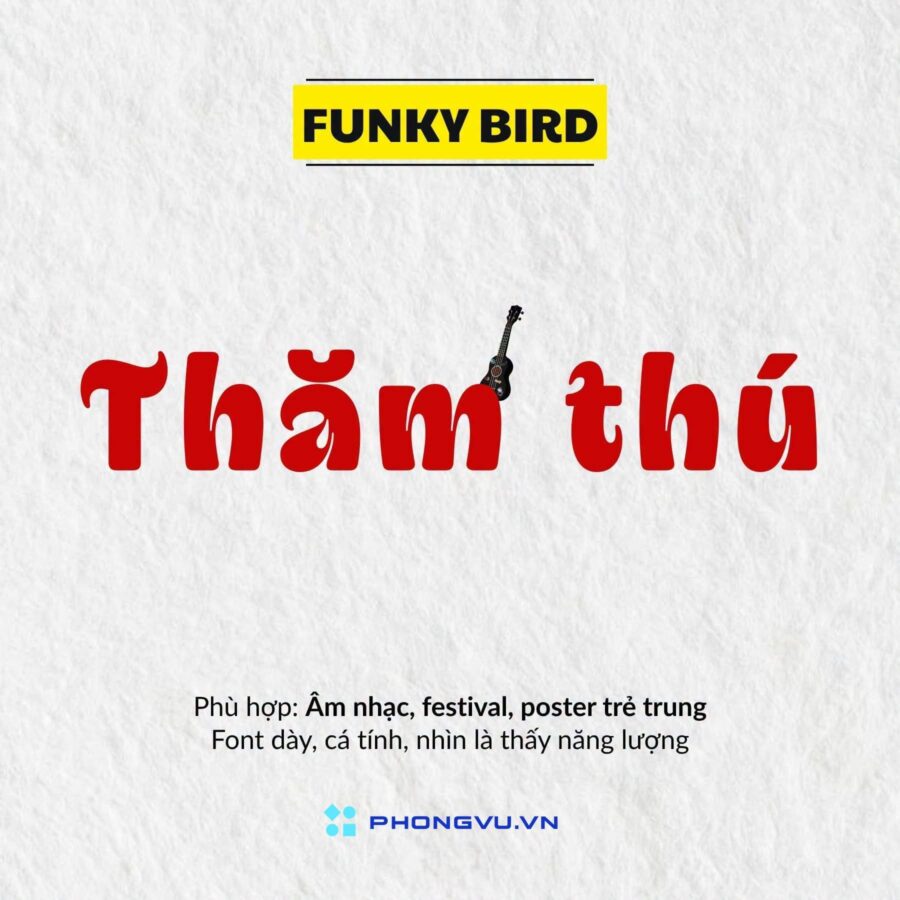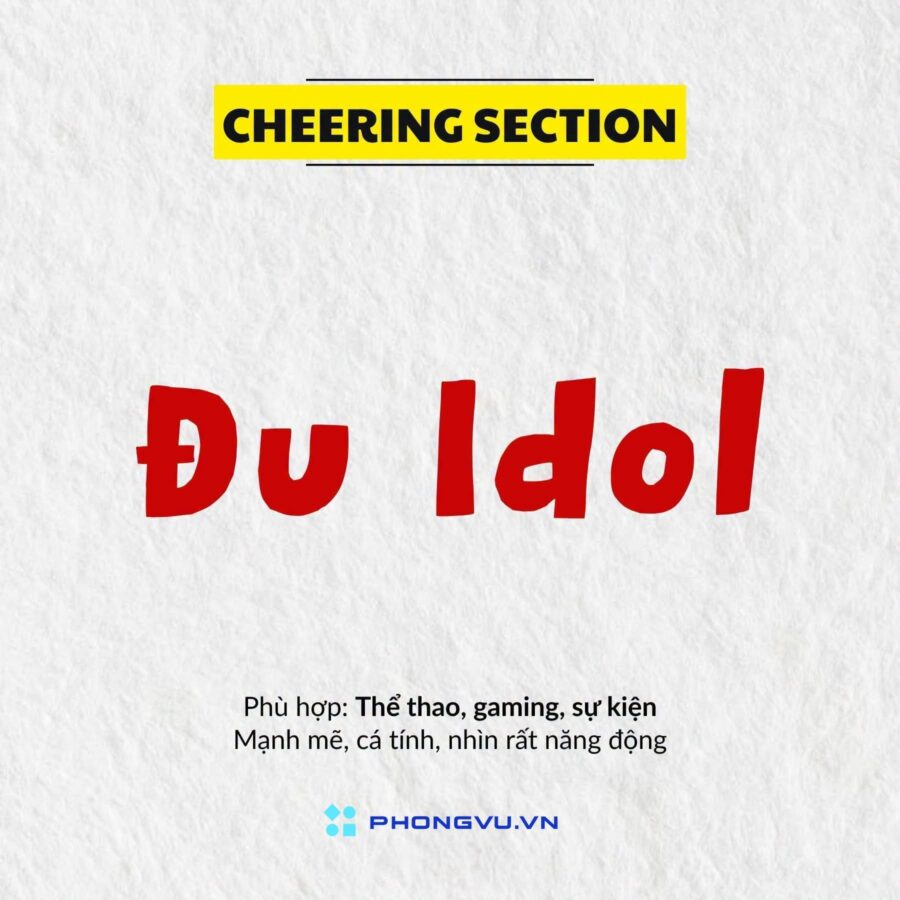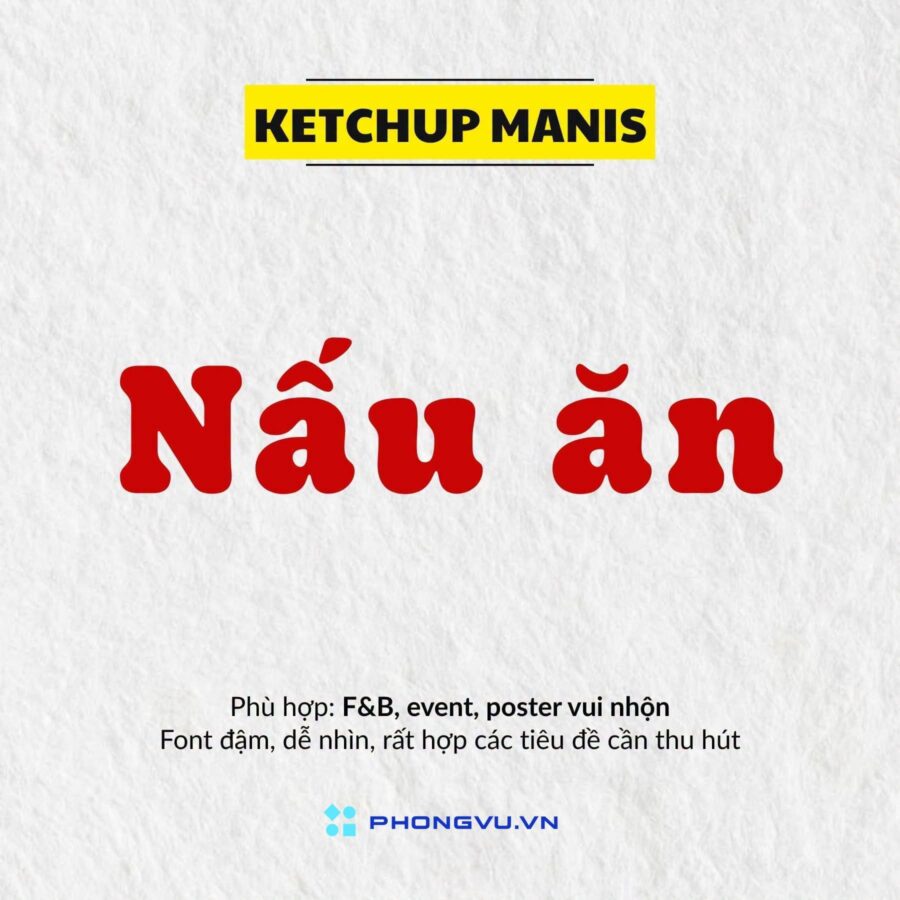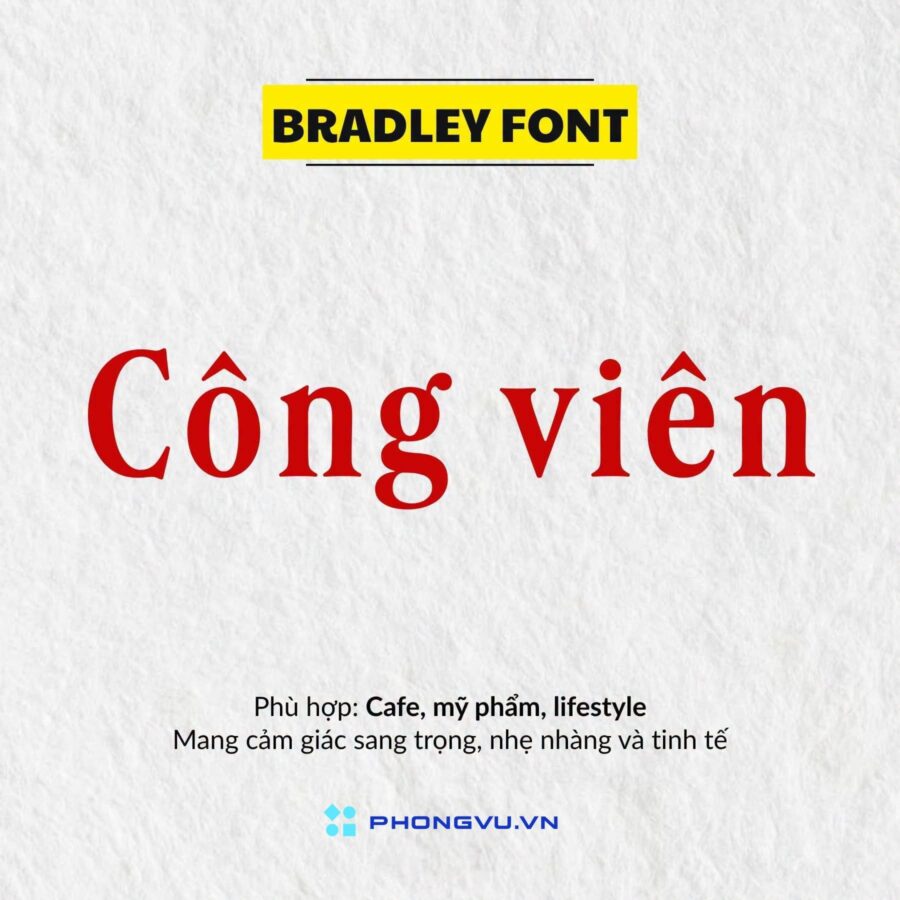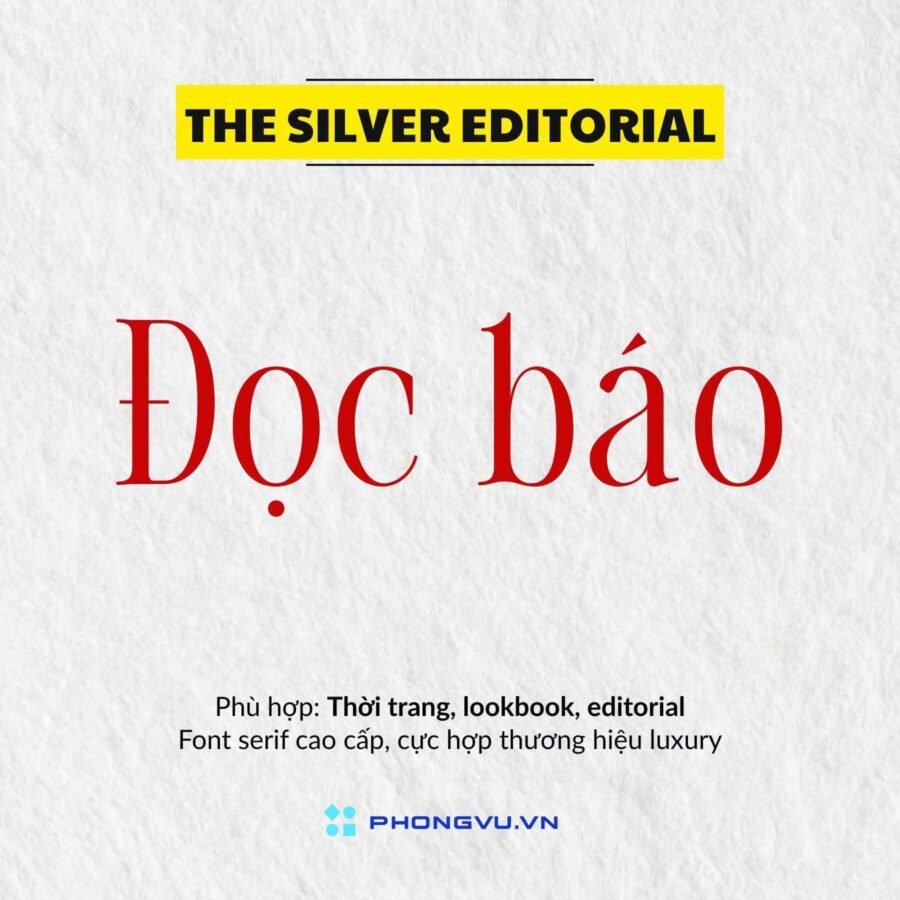
Bạn đang tìm kiếm những font chữ Việt hóa trên Canva đẹp, độc đáo và dễ sử dụng trên để nâng tầm thiết kế của mình? Với sự phát triển không ngừng của nền tảng Canva và nhu cầu sáng tạo nội dung ngày càng cao, việc sở hữu những font chữ chất lượng không chỉ giúp bạn thể hiện phong cách cá nhân mà còn tối ưu hóa trải nghiệm người xem. Trong bài viết này, Phong Vũ Tech News đã tổng hợp và chọn lọc danh sách 111+ font chữ Việt hóa mới nhất năm 2026, đảm bảo đáp ứng mọi nhu cầu từ thiết kế thương hiệu, bài thuyết trình, đến các dự án nghệ thuật. Hãy cùng khám phá để làm mới kho ý tưởng của bạn ngay hôm nay!
I. Top các Font chữ Việt hóa trên Canva đẹp, chuyên nghiệp
Trong kho tàng font chữ phong phú của Canva, việc tìm ra những font chữ Việt hóa vừa đẹp mắt, vừa chuyên nghiệp đôi khi có thể khiến bạn bối rối. Để giúp bạn tiết kiệm thời gian và tối ưu hóa thiết kế của mình, chúng tôi đã lựa chọn những font chữ Việt hóa trên Canva nổi bật nhất, phù hợp với nhiều phong cách và mục đích sử dụng như sau:
- Amatic SC
- Pacifico
- Coiny
- Vollkorn
- Blacker Sans Text
- Mali
- Dancing Script
- Noto serif display black
- Bahianita
- Sigmar one
Từ những font thanh lịch dành cho thương hiệu cao cấp, đến các kiểu chữ sáng tạo cho bài thuyết trình hay nội dung truyền thông mạng xã hội, danh sách tên sẽ là người bạn đồng hành không thể thiếu cho các dự án của bạn.
III. Bí quyết tìm các Font chữ Việt hóa trên Canva đẹp nhất
Việc lựa chọn font chữ phù hợp có thể quyết định phần lớn thành công của thiết kế. Đặc biệt, với những font chữ Việt hóa, yếu tố thẩm mỹ và hỗ trợ tiếng Việt đầy đủ là rất quan trọng. Dưới đây là những bí quyết giúp bạn dễ dàng tìm được các font chữ Việt hóa trên Canva đẹp và ấn tượng nhất:
- Bước 1: Tìm kiếm bằng từ khóa: Gõ “Sans Serif” hoặc “Slab Serif” vào ô tìm kiếm. Trong đó, Sans Serif: Font không có chân, thường dùng cho thiết kế hiện đại, trẻ trung. Slab Serif: Font có chân vuông, tạo cảm giác chắc chắn, chuyên nghiệp. Đây là hai loại font phổ biến và dễ đọc với tiếng Việt.
- Bước 2: Chọn font ưng ý: Canva sẽ hiển thị nhiều tùy chọn. Bạn có thể lọc theo độ đậm nhạt, kiểu chữ (in hoa, thường) để tìm font phù hợp nhất.
IV. Một số câu hỏi thường gặp về các Font chữ Việt hóa trên Canva
Trong quá trình thiết kế, đặc biệt khi sử dụng các font chữ Việt hóa trên Canva, bạn có thể gặp một số thắc mắc về cách chọn font, xử lý lỗi hoặc tùy chỉnh font theo ý muốn. Dưới đây, chúng tôi đã tổng hợp và giải đáp những câu hỏi thường gặp nhất để giúp bạn dễ dàng hơn trong việc sử dụng font chữ trên Canva:
1. Font chữ Việt hóa trên Canva và chưa Việt hóa có gì khác nhau?
Font chữ Việt hóa là những font đã được điều chỉnh để hỗ trợ đầy đủ các ký tự tiếng Việt, bao gồm cả các dấu (sắc, huyền, hỏi, ngã, nặng) và chữ cái đặc biệt như “ă”, “â”, “ê”, “đ”,… Những font này đảm bảo tính thẩm mỹ, độ cân đối khi sử dụng cho văn bản tiếng Việt.
Ngược lại, font chưa Việt hóa thường chỉ hỗ trợ ký tự cơ bản của bảng chữ cái tiếng Anh. Khi sử dụng cho tiếng Việt, các dấu và chữ cái đặc biệt có thể bị lỗi như mất nét, hiển thị không đồng đều hoặc thay bằng ký tự lạ. Điều này làm giảm chất lượng thiết kế và tính chuyên nghiệp của sản phẩm.
2. Làm sao để Việt hóa font chữ trên Canva?
Hiện tại, Canva chưa có tính năng trực tiếp để Việt hóa font chữ. Tuy nhiên, bạn có thể thực hiện theo các cách sau:
- Tìm bản Việt hóa của font chữ: Rất nhiều nhà thiết kế và cộng đồng trực tuyến đã Việt hóa các font phổ biến. Hãy tìm kiếm tên font kèm từ khóa “Việt hóa” để tải về phiên bản hỗ trợ tiếng Việt.
- Sử dụng font chữ Việt hóa có sẵn: Canva cung cấp một kho font chữ khổng lồ, trong đó có nhiều font chữ Việt hóa đẹp mắt. Bạn chỉ cần tìm kiếm và chọn font chữ phù hợp với thiết kế của mình.
- Tải font chữ Việt hóa lên Canva: Nếu bạn có font chữ Việt hóa yêu thích, bạn có thể tải lên Canva để sử dụng. Tuy nhiên, tính năng này thường chỉ dành cho các tài khoản Canva Pro hoặc các gói cao cấp hơn.
3. Làm sao để tải font chữ lên Canva?
Nếu bạn đang sử dụng phiên bản Pro, việc tải font chữ Việt hóa trên Canva rất đơn giản:
- Bước 1: Chuẩn bị font chữ: Đảm bảo font chữ của bạn có định dạng .ttf hoặc .otf và đã được Việt hóa nếu dùng cho tiếng Việt.